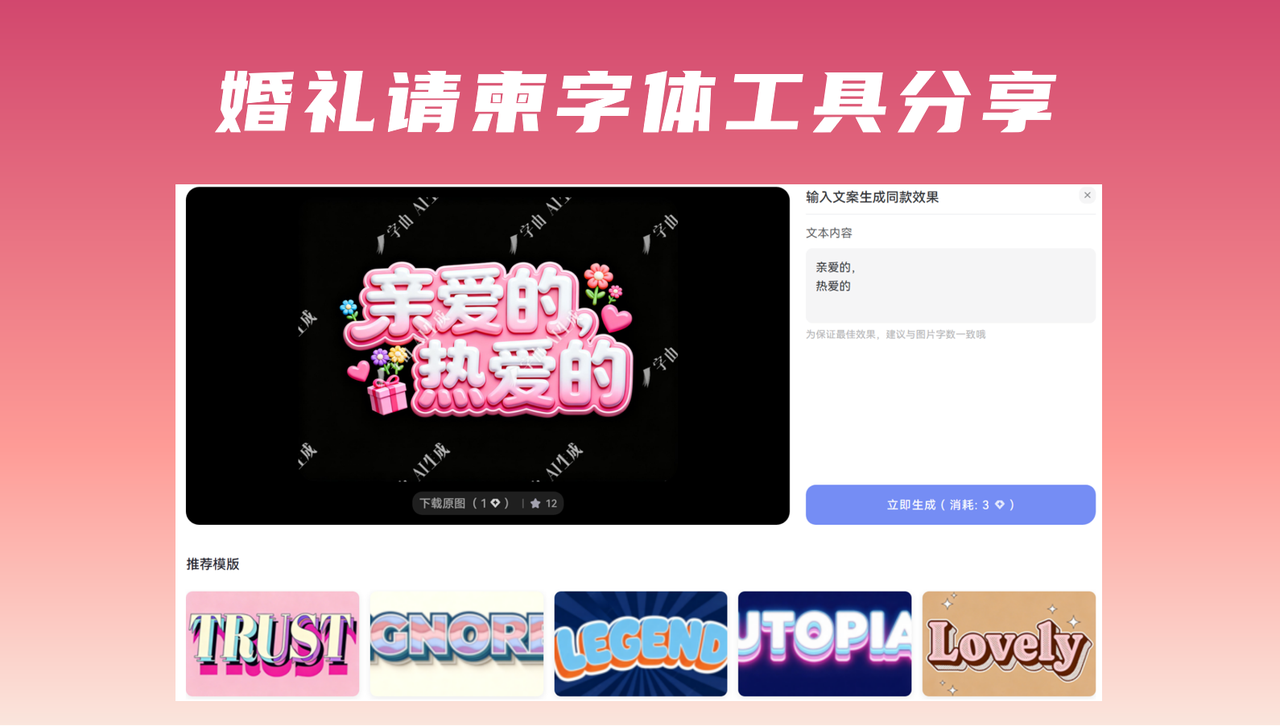
教你制作婚礼请柬字体,小众高级不撞款
备婚时总纠结婚礼请柬不够特别?其实不用在材质和装饰上过度花费,选对字体就能自带高级感——请柬是爱情的第一份官宣,更是宾客对婚礼的初印象,比起宋体、黑体这种随处可见的通用款,小众有质感的字体,才能藏住你们的独特格调,把浪漫说进细节里。很多新人怕自己不会设计,今天我就分享4个亲测好用的婚礼请柬字体网站,手把手教你搞定婚礼请柬字体。
一、字由网
优先给新手安利字由网,也是我帮朋友们制作婚礼请柬时反复用的字体工具,下载客户端就能直接操作,兼顾实用性和小众感,性价比拉满,新手闭眼冲不踩雷。
制作婚礼请柬字体的第一种方法就是直接使用字由网的免费商用字体,种类也有很多,可以根据你婚礼请柬的风格自行挑选。比如,办中式婚礼的话,楷书、隶书、毛笔行书这些古典字体随便挑,笔画间的东方韵味刚好适配“囍”字、新人姓名和古风邀请语,贴合传统喜帖的礼仪感。
西式婚礼能挖到优雅衬线体、流畅手写体,搭配英文落款,氛围感直接拉满;偏爱极简风的话,各类无衬线字体简洁利落,不会显得拖沓,适配简约款请柬。
第二个方法就是利用字由的AI字体功能,从字由官网顶端菜单栏中的“字体工具”进入,我们能看到有很多的AI字体模板。
当然,如果确定好自己婚礼请柬风格的话,也可以从风格分类中快速筛选到自己想要的字体风格,风格多样,适用于各种场景。
点击心仪的字体模板,在右侧文本框内输入想要生成的字体。但是要注意:输入的字体字数要与模板上的字体数一致哦~点击立即生成,等待几秒就能得到同款字体啦。
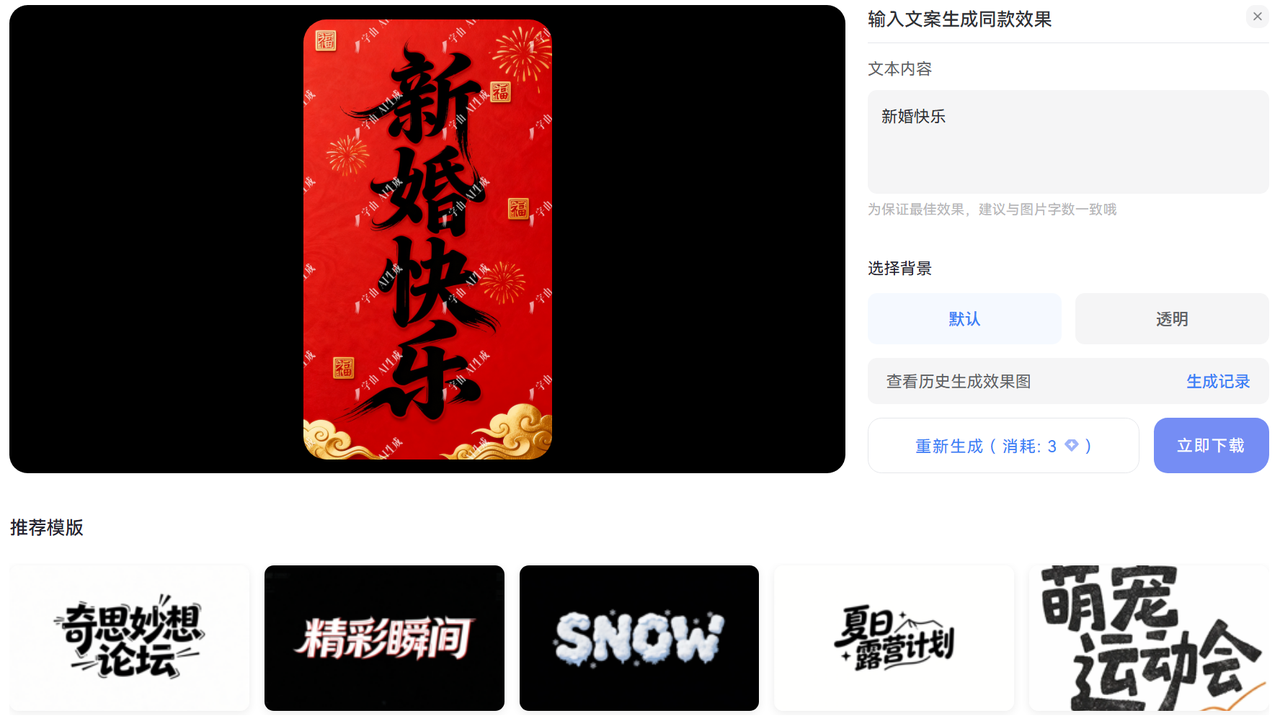
如果平时刷到好看的请柬字体却不知道名字,还有个超实用的AI字体识别功能,直接上传图片就能识别,再也不用全网蹲答案。
二、创客贴
如果不想单独做婚礼请柬字体设计,还想快速搞定整个请柬排版,创客贴绝对是最优解。它的核心优势就是婚礼请柬字体和请柬模板深度绑定,不用自己费心搭配。内置上千款可商用字体,中式复古的毛笔字、隶书,西式浪漫的衬线体、连笔手写体,还有小众创意的肌理装饰字体全都有,刚好适配不同风格的婚礼。不管是发电子请柬,还是打印纸质请柬、回执卡都适配,高效又靠谱,赶进度的新人可以直接冲。
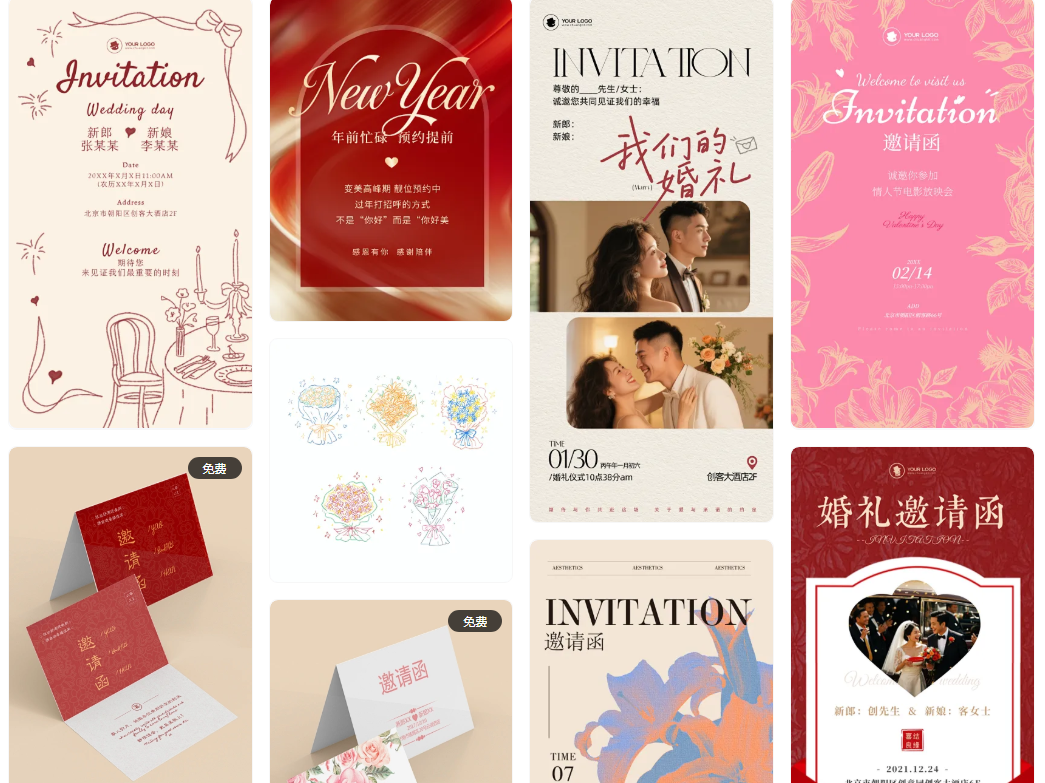
三、Calligraphy Font Generator
筹备西式婚礼、森系婚礼,或者想在请柬上加英文落款的新人,一定要收藏这个网站。它是专门做西文书法字体的免费工具,主打手写感和优雅感,字体小众不撞款,用来做请柬标题、新人英文名,瞬间拉满浪漫氛围,比通用西文字体有质感多了。整个流程下来不超过5分钟,输入文字、选风格、调参数、导出,三步就能搞定,哪怕是第一次用,也能快速上手,适合偏爱西式浪漫感的新人。
四、FontSpace:小众字体合集,解锁独家质感
FontSpace它不是单纯的字体生成工具,更像是设计师原创字体合集,收录的大多是市面上不常见的原创字体,用来做婚礼请柬字体,能轻松打造专属格调。字体分类很清晰,能按风格、用途、设计师筛选,不用在海量字体里浪费时间。很多字体都是设计师原创,使用频率极低,能有效避免婚礼请柬字体款。适合追求个性化、不想随波逐流的新人,用来做桌号牌、婚礼菜单的字体也很合适。
不用懂专业设计,不用花大价钱请人定制,简单几步就能做出不撞款的高级婚礼请柬字体,让请柬从细节处彰显你们的格调,把浪漫藏进每一个字体里,给宾客留下深刻印象,也为自己的婚礼留下一份专属纪念。